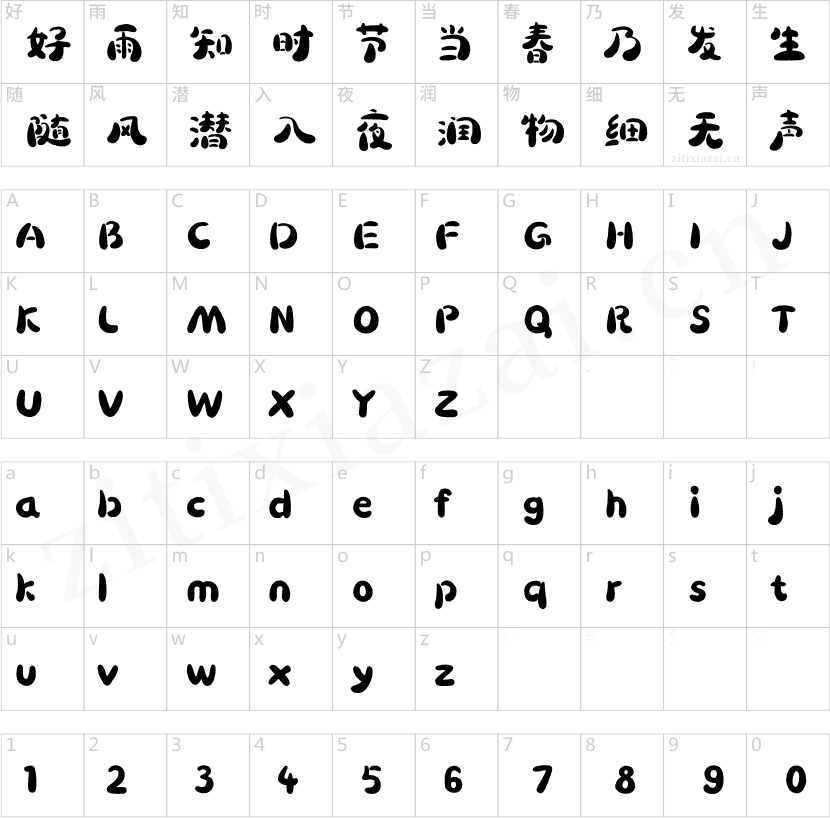
汉仪熊猫体
汉仪熊猫体,这款字体结构工整、笔画清晰,兼顾美观与易读性,适用于标题、正文、海报、包装、LOGO 等多种场景。字形优雅稳定,风格百搭耐看,适配日常排版与创意设计,让文字呈现更舒适、更具质感。汉仪熊猫体一笔一画,皆是细节,以均衡的比例、流畅的线条打造舒适视觉体验,字形端正大气,风格简约现代。无论是商业设计、品牌宣传还是日常排版,都能轻松驾驭,让文字更有格调与力量。汉仪熊猫体字体下载。
• 字体说明:汉仪熊猫体是一款承载了蜀文化的书写字体,以写意的手法使得熊猫形象跃然纸上,无需具象的细节描绘,凭借书写的笔法和状态令人联想到憨态可掬的川地熊猫、茂密清幽的竹林云海、烟雾缭绕的火锅小吃和悠闲轻松的蜀人生活哲学。作为一款寓巧于拙的书写标题字体,适合应用于影视娱乐、休闲文旅、食品餐饮、书籍绘本、展览广告等使用场景,渲染自然的生命力和生活的烟火气。汉仪熊猫体的书写不止于字体,有着更广大的愿景:那就是成为四川的文字符号和字体印象。